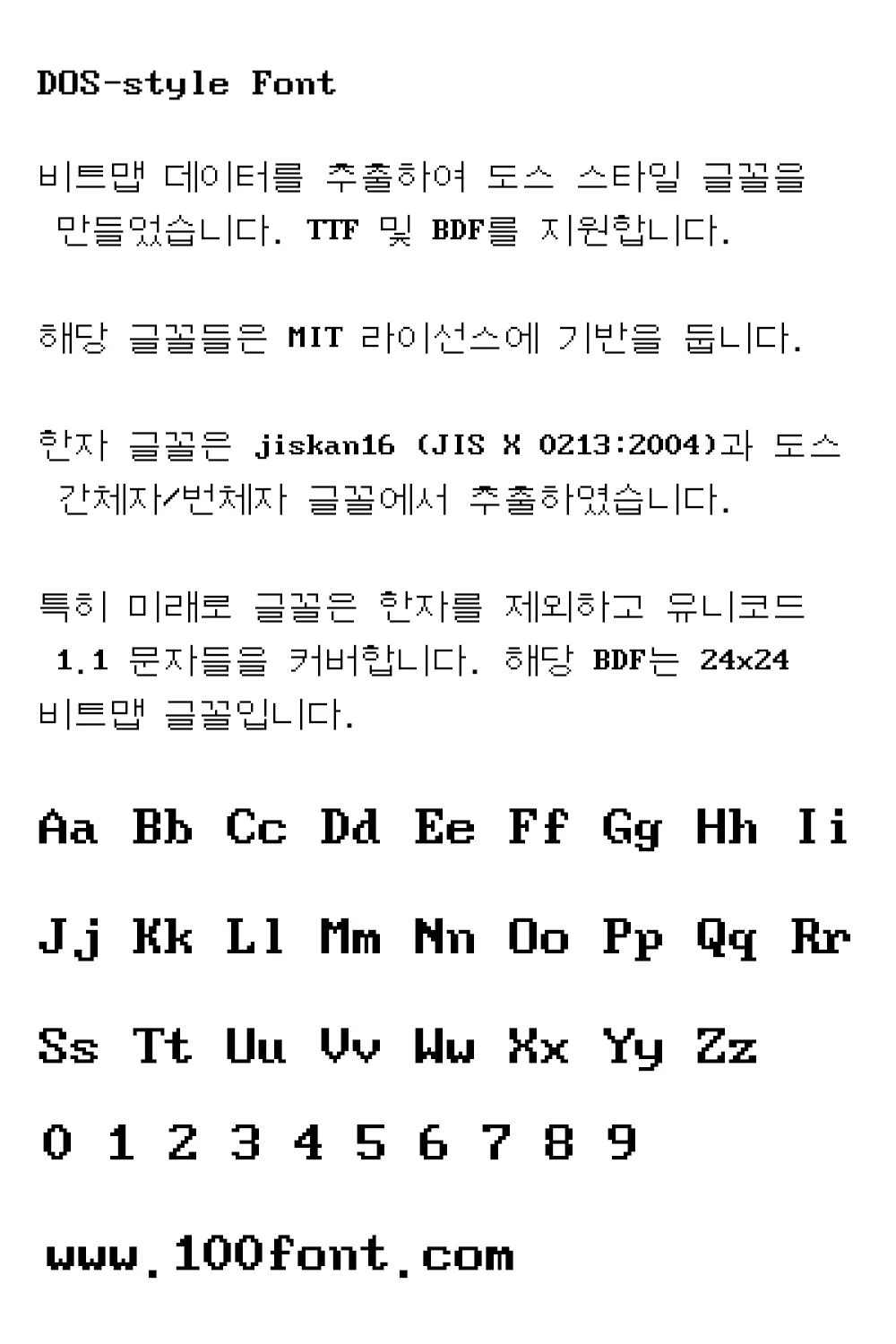
hurss系列像素字體是由韓國的Damheo Lee用位圖二進制數據創建的一系列DOS風格像素字體,採用The MIT License(麻省理工學院許可證)發佈,這套字體有TTF和BDF兩種格式,TTF格式可以在Windows系統中使用,BDF格式可以在Linux終端中使用。
CJK表意文字是從Hanme-hangul(KS X 1001 Hanja;DOS中的一種hangul輸入法)和jiskan16輸入的(https://ja.wikipedia.org/wiki/Jiskan)(JIS X 0213:2004漢字);由日本電子和信息技術產業協會的Imamura和Hanataka設計。儘管如此,我們仍需要解決一些小問題。
特別是,Miraero Normal字體只包含Unicode 1.1字形,不包含CJK表意文字。它的BDF是24×24位圖字體。
DOSMyungjo (도스명조)
DOSGothic (도스고딕)
DOSSaemmul (도스샘물)
Sam3KRFont (삼국지3글꼴) – 한자 없음 (Not contains Hanja), MS워드 사용시 자간 뭉개질 수 있음
MiraeroNormal (미래로 글꼴) – KS X 1001 & KS X 1002 한자 (KS X 1001 & KS X 1002 Hanja), Unicode 1.1 glyphs and Euro Sign Support
DOSIyagiBoldface (도스이야기) – 이야기 굵은체
DOSPilgi (도스필기)